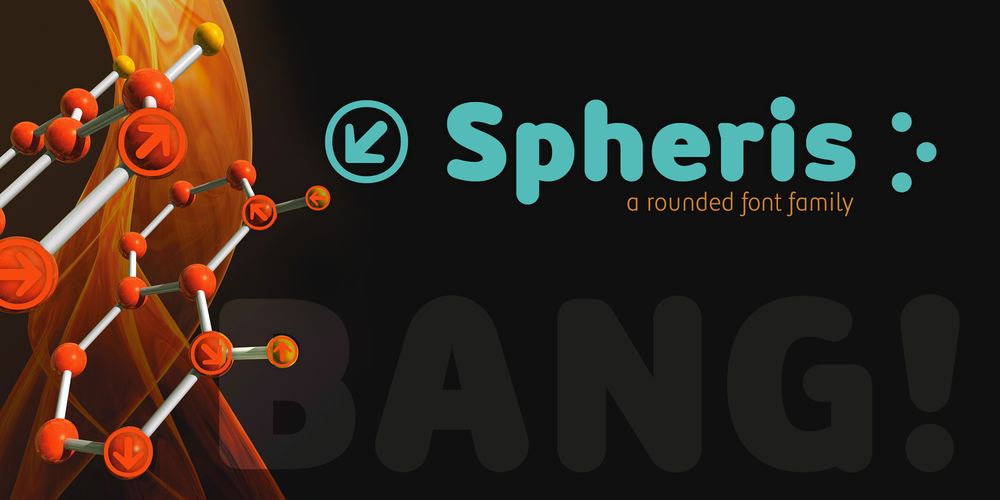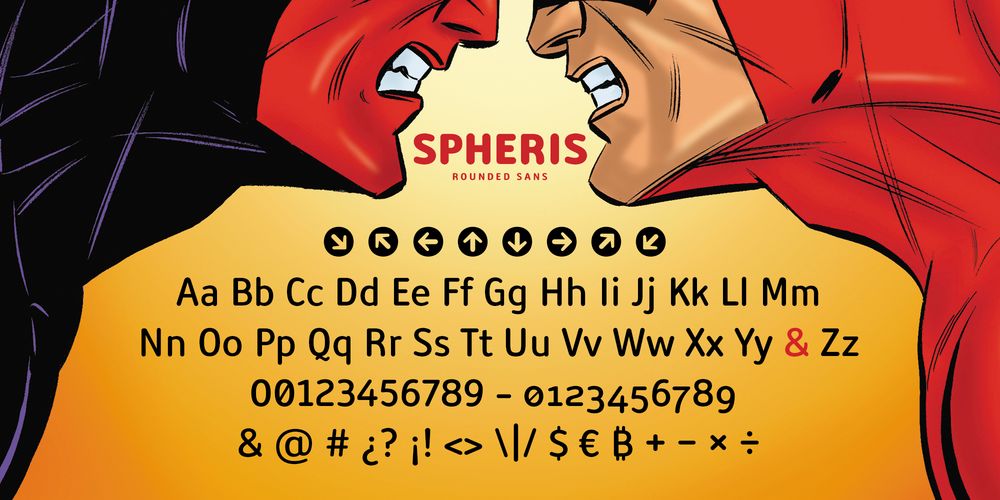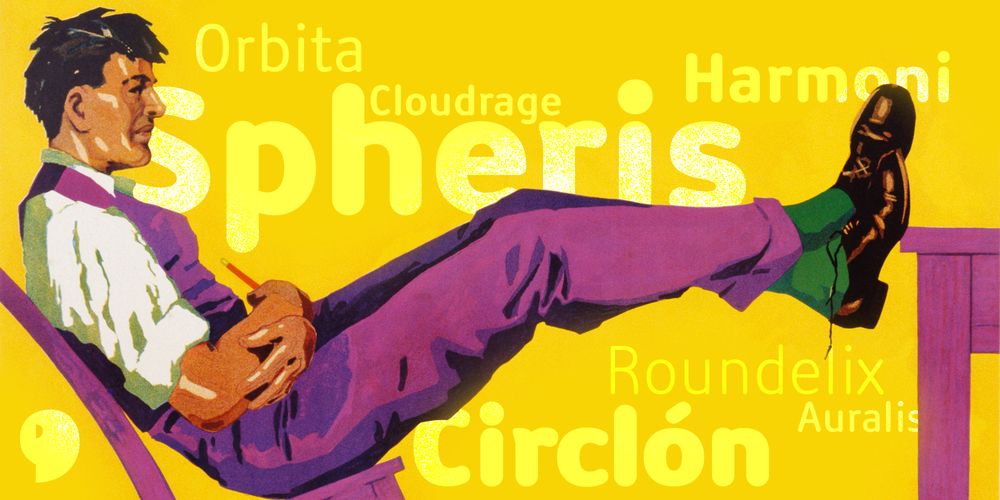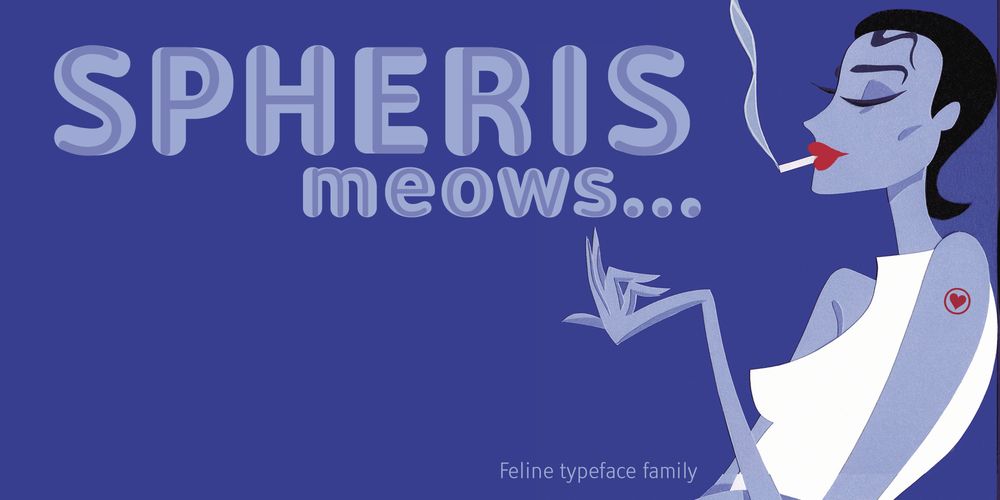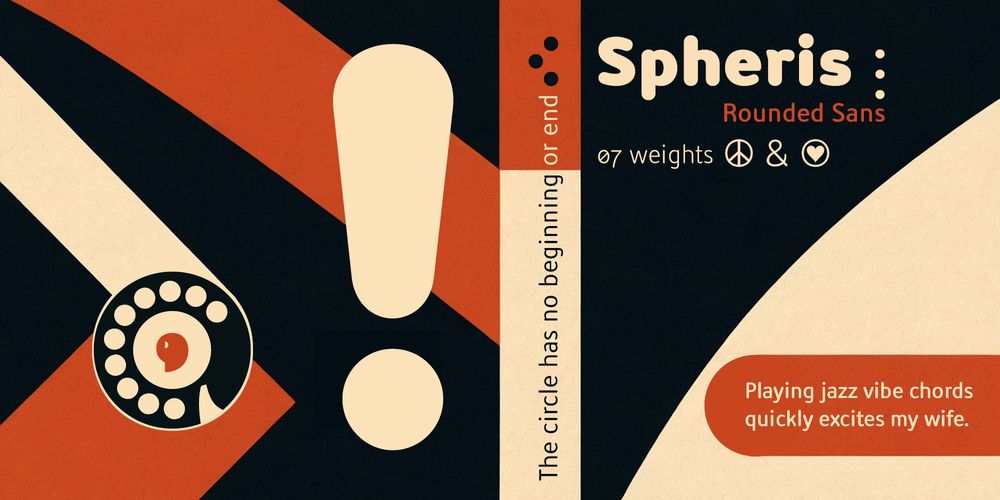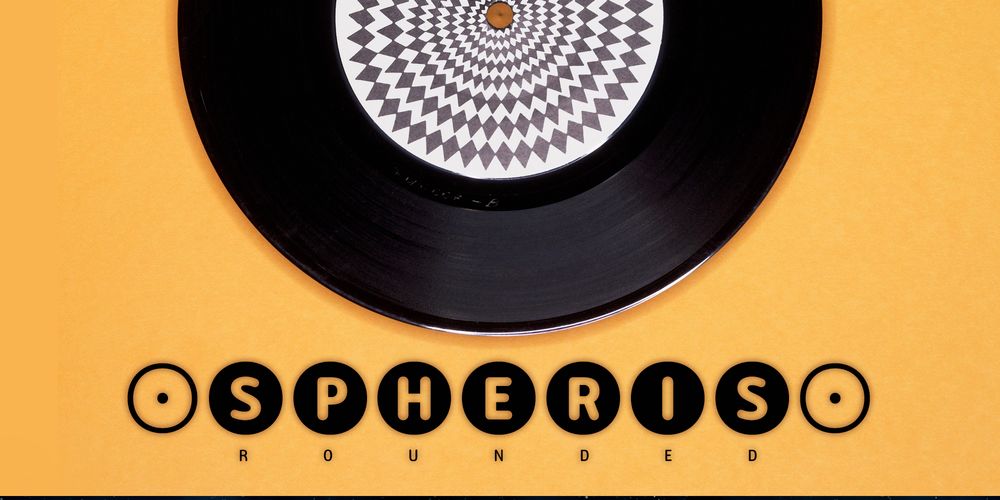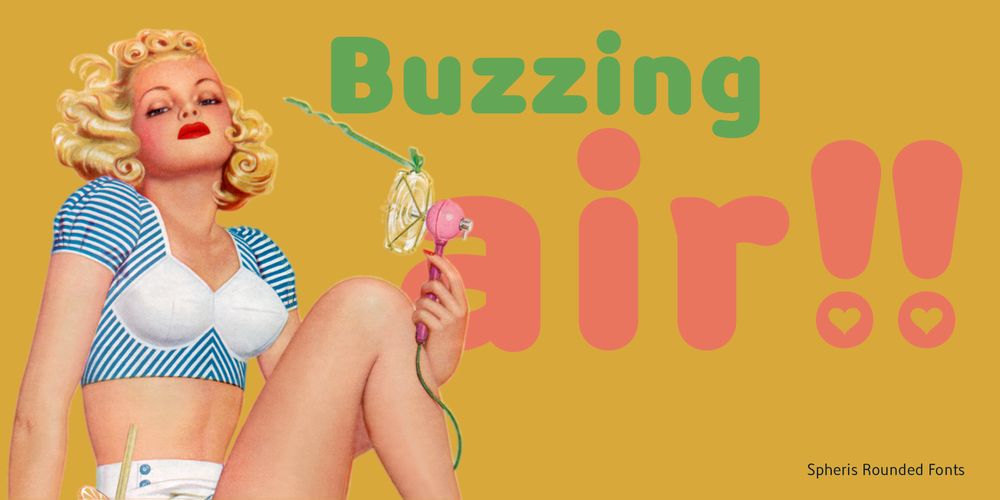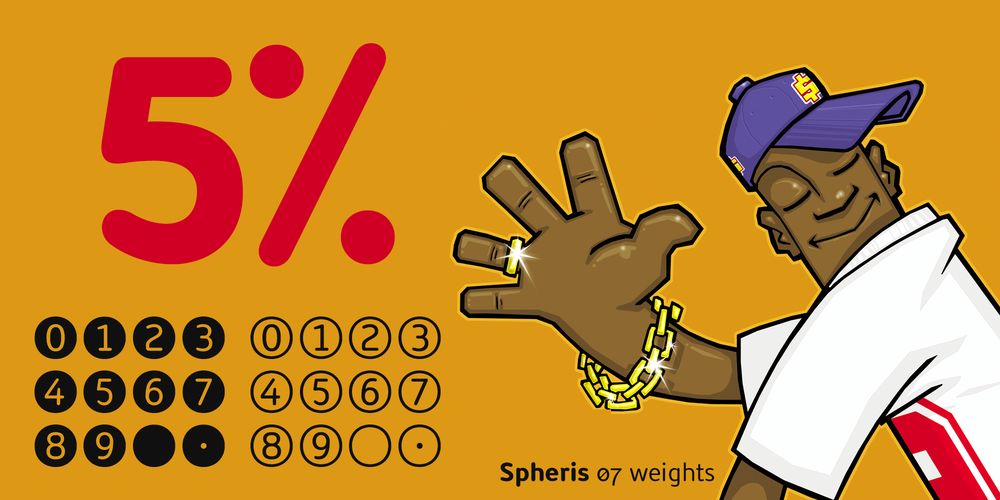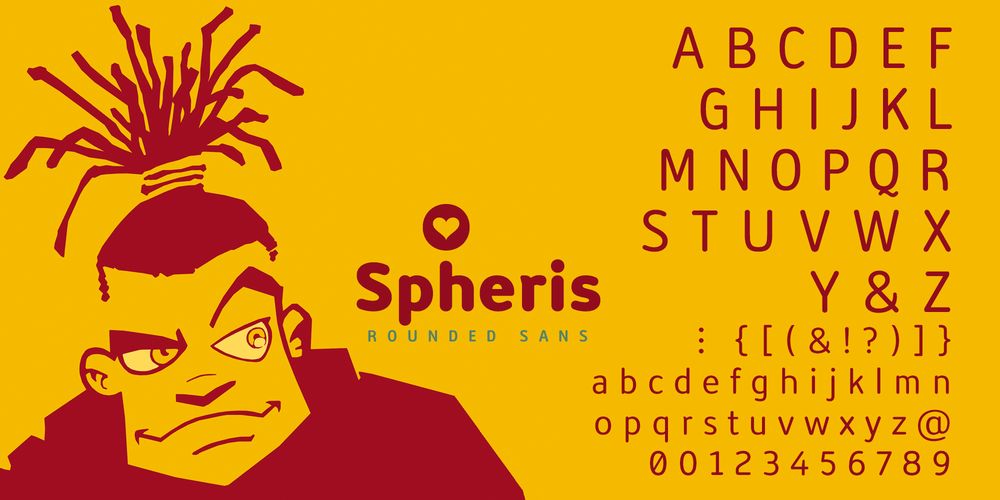
Sans & Round | 07 Typefaces
Estilo: Round, Sans Serif, Display, Geometric
Proporción: Light, Regular, Medium, Semi Bold, Bold, Extra Bold, Black
Glyphs: 821
Alternates: 193
Latin-Extended: Latín Básico, Europa Occidental, Central & Oriental.
Autor: deFharo
Funciones OpenType: Additional languages, All Alternates, Bitcoin, Capital Spacing, Contextual Alternates, Denominators, Discretionary Ligatures, Fractions, Historical Forms, Inferiors, Kerning, Localized Forms, Numbers Small Caps, Numerators, Oldstyle Figures, Ordinals, Scientific Inferiors, Slashed Zero, Standard Ligatures, Stylistic Set, Subscript, Superior letters, Superiors, Superscript.
821 glyphs w/ 193 alternates: Numbers, Signs & Letters
Spheris: Geometría que respira
Spheris nace de una contradicción deliciosa: una sans serif geométrica con vértices redondeados que parecen respirar.
Como diseñador freelance, siempre he tenido una obsesión: encontrar el equilibrio entre lo humano y lo geométrico. Las tipografías sans serif redondeadas habitan precisamente ese territorio ambiguo—ni frías ni blandas, ni técnicas ni ingenuas. Son sistemas… pero también son piel.
Con Spheris, he querido llevar esa dualidad al límite. Trabajo en ese punto exacto donde la forma deja de ser solo forma… y empieza a sentirse.
Una tipografía diseñada para fluir
Spheris es una familia sans serif geométrica redondeada. Sus curvas no son un gesto decorativo: son una decisión estructural. Cada terminal suavizado, cada arco cuidadosamente medido, está ahí para construir una lectura fluida, casi táctil. Es una tipografía que no se impone: te acompaña.
Cada métrica y cada ajuste de kerning han sido configurados para que el ritmo de lectura no sea simplemente funcional, sino natural y placentero. No se trata solo de leer; se trata de deslizarse a través de las palabras.
Aquí no hay aristas que hieran. Cada terminal, cada remate, cada ojo cerrado de la “a” o la “e” es una pequeña promesa de claridad con carácter. Porque lo redondeado no es débil: es estratégico.
Lo que trae Spheris
Con siete pesos que van del etéreo Light hasta el gravitacional Black, Spheris es un universo tipográfico completo.
Cada variación ha sido esculpida no solo cambiando el grosor del trazo, sino recalibrando las tensiones internas, ajustando esos puntos de tangencia donde la recta se rinde ante la curva.
– El resultado es una familia que baila en perfecta sincronía:
- Light: delicadeza aérea para textos sutiles.
- Regular, Medium & Semi Bold: el latido constante de cualquier identidad visual.
- Bold, Extra Bold & Black: fuerza y presencia amable.
Detalles que marcan la diferencia
Arquitectura de caracteres
— Permiten crear jerarquías invisibles pero perceptibles, aportando una versatilidad excepcional.
- 03 juegos de Mayúsculas.
- 05 juegos de minúsculas.
- 02 juegos de flechas.
- 193 caracteres alternativos.
Estos elementos actúan como susurros visuales: desde flechas elegantes hasta signos de puntuación especiales como tricolon, asterism, referencemark, etc. Puntuación con intención.
Un Arsenal Creativo
Spheris está viva. Gracias a sus funciones avanzadas OpenType, se adapta tanto a necesidades técnicas como expresivas.
Los símbolos monetarios internacionales y las criptomonedas están ahí. Y esos juegos de flechas en círculos negros y blancos… son poesía funcional para wayfinding y sistemas de señalización.
- Fracciones automáticas que se construyen de forma natural.
- Ordinales que fluyen naturalmente; numeradores y denominadores para composición científica y editorial.
- Símbolos monetarios y criptomonedas, del euro al bitcoin.
- Ligaduras estándar y discrecionales mejoran la fluidez del texto.
- Signos de puntuación decorativos
Tricolon, referencemark, dotted cross, asterism, therefore, because… signos con personalidad propia. - Alternate Annotation Forms
Estilos black circle y circle white, donde números, letras y flechas adquieren una presencia icónica. Perfectos para señalética e infografías. - Alternativas contextuales de puntuación
La puntuación se adapta sin romper el flujo del texto.
Todo ello bajo el soporte de Latin Extended-A.
Spheris. Redondeada. Geométrica. Humana.
Spheris no pretende reemplazar tu sans serif favorita. Quiere convivir con ella… y elevar lo que haces.
Funciona especialmente bien en:
- Diseño editorial que necesita seducir página tras página.
- Folletos que invitan a ser conservados.
- Cartelería que detiene la mirada.
- Identidades visuales duraderas.
- Packaging que comunica calidad y calidez.
- Señalética clara, elegante y sin estridencias.